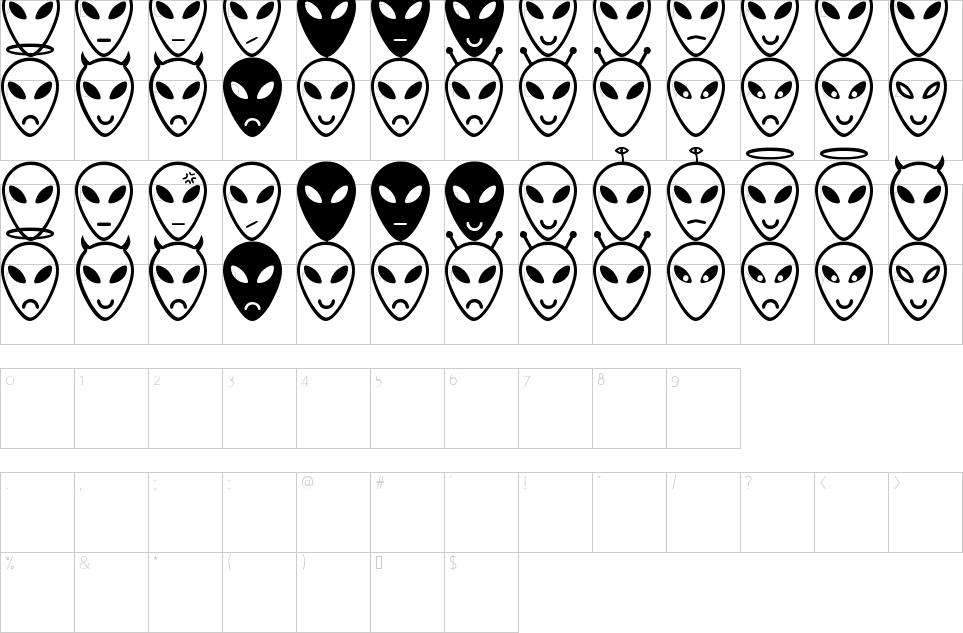
Alien Faces é uma fonte gráfica de caráter único que traz uma atmosfera desconcertante e envolvente. Inspirada na cultura do horror e do estranho, esta fonte é um ótimo adorno para qualquer projeto que exija um toque inusitado. Ela foi criada pela designer Southype, e já tem 23.332 downloads. É uma fonte divertida e inovadora que oferece um toque único à qualquer projeto digital. Não importa se você está criando uma campanha de marketing, uma arte digital ou até mesmo um design para uma camiseta, Alien Faces trará uma cara desconcertante e única para seu projeto. Não deixe de adicionar um toque estranho e único ao seu design com Alien Faces.